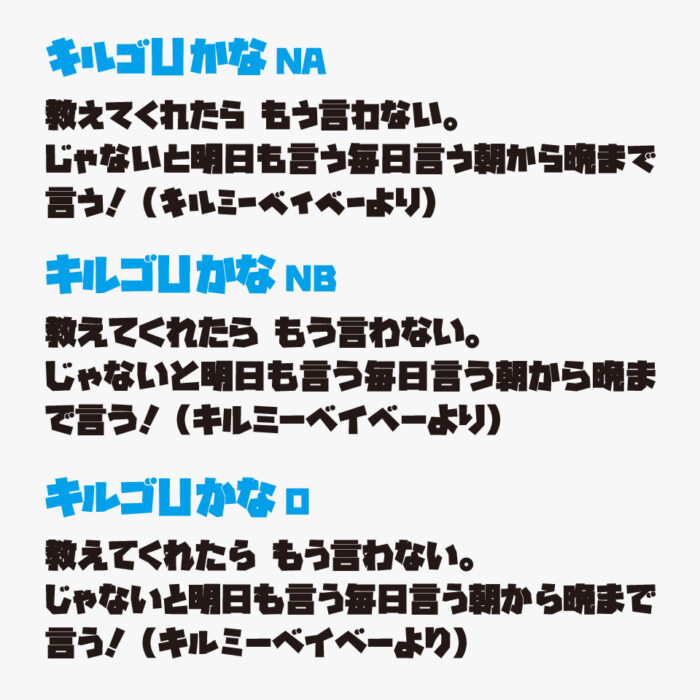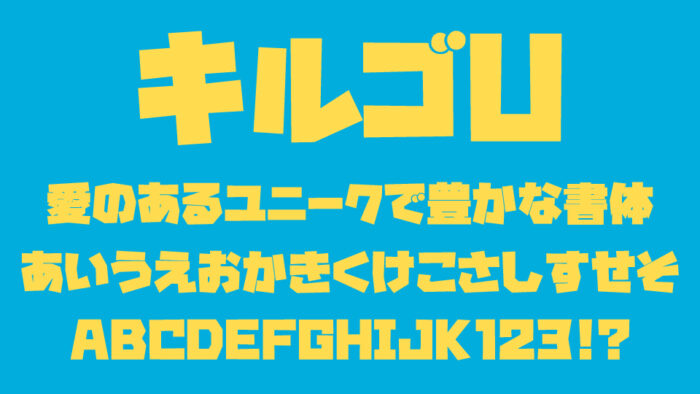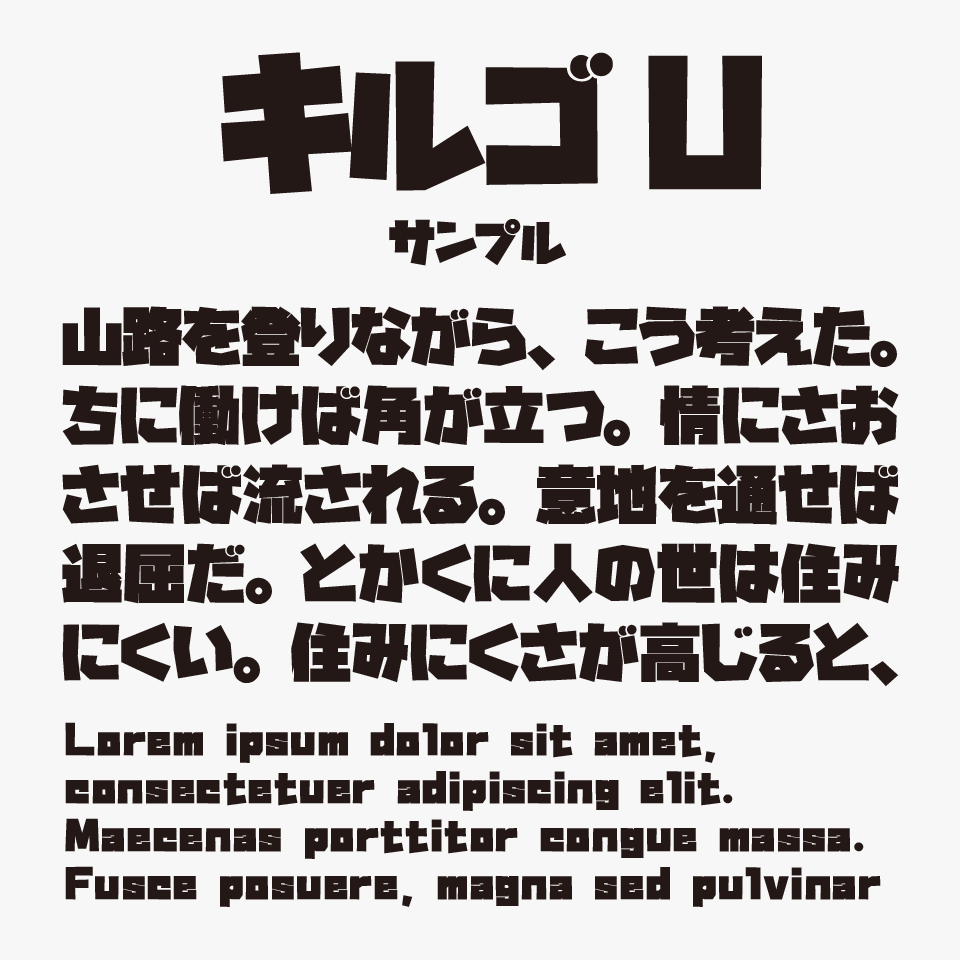
キルゴUフォントは、人気マンガ「キルミーベイベー」のタイトルロゴから着想を得てに制作された超極太スタイルのデザインフォントです。
ロゴの雰囲気をそのままに、少しだけ遊び心が加えられており、とってもキャッチーな仕上がりになっているデザインです。ゴツゴツしたフォルムがポップで元気な印象がでるので、バナーや動画アイキャッチなどのタイトルやキャッチコピーに使うとインパクトがでるフォントです。
ひらがな・カタカナのデザインが違うバリエーション「キルゴUかなNA・キルゴUかなNB・キルゴUかなo」が用意されています。どのバリエーションもまた違った雰囲気があって良いですね。
キルゴUかなNAがロゴに違いデザインとなっているようです。
収録文字は、カタカナ・数字・一部記号・ひらがな・アルファベット・ロシア文字・ギリシャ文字と漢字3087文字が収録されています。